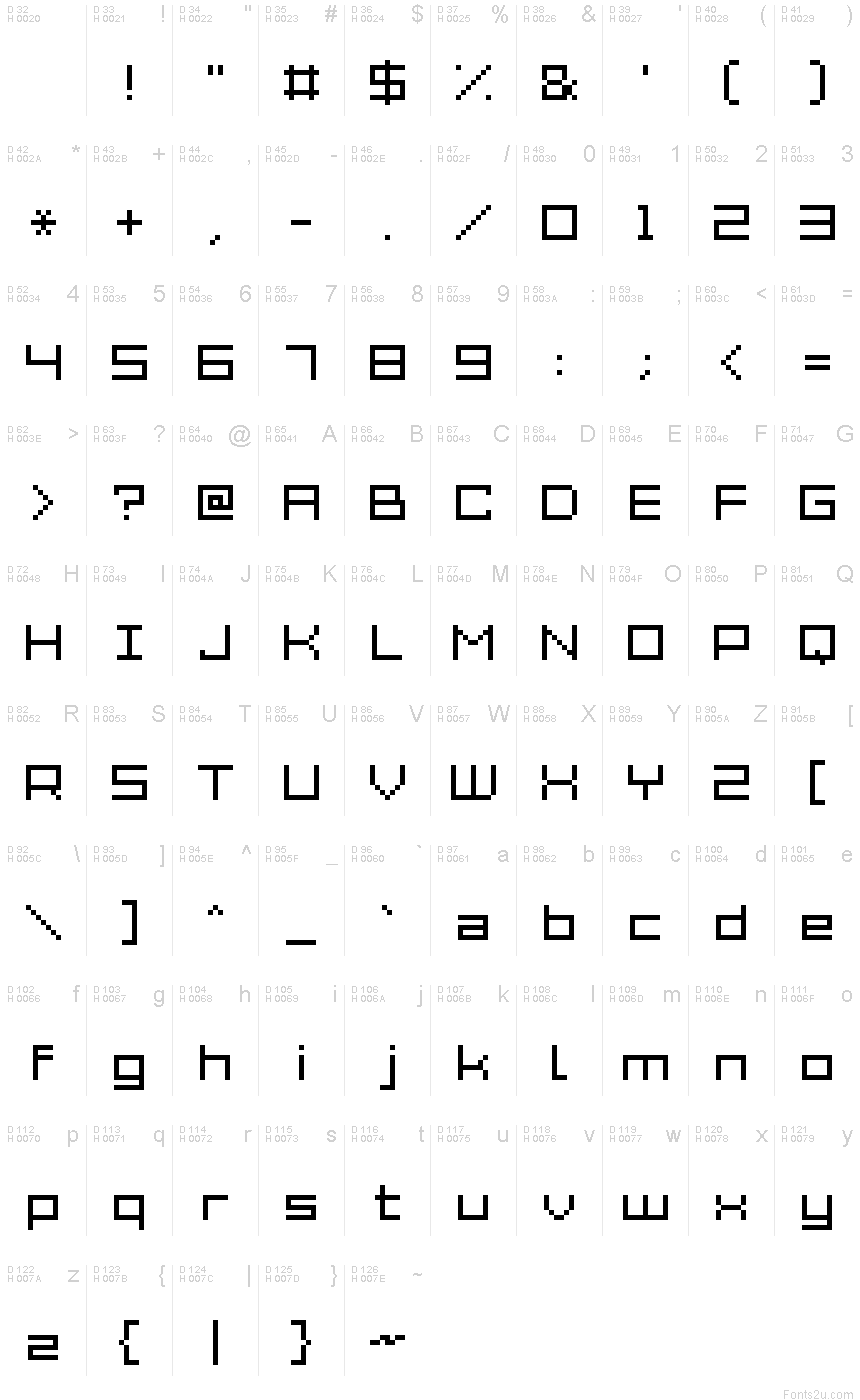
Grixel Acme 7 Wide Xtnd
Grixel Acme 7 Wide Xtnd od Grixel - Greek Pixel Fonts to darmowy, pixelowy krój bitmapowy o wyraźnej, rozciągniętej estetyce, nawiązującej do przewijanych ekranów gier. Jego bardzo szerokie proporcje, ostre pociągnięcia o grubości jednego piksela i ciasny rytm nadają każdemu słowu charakter migającego banera – niczym zamrożona w ruchu klatka z ekranu demonstracyjnego retro. Litery pozostają niezwykle czytelne nawet przy bardzo małych rozmiarach, dzięki czemu uzyskujesz ostrą, rastrową teksturę bez zbędnego szumu wizualnego.
Dzięki Grixel Acme 7 Wide Xtnd nadasz spójny, futurystyczny klimat interfejsom gier retro (HUD), logotypom sci-fi, plakatom vaporwave, stronom z pixel artem, nakładkom do streamowania oraz okładkom albumów synthwave. Ten darmowy font świetnie sprawdza się w krótkich hasłach lub etykietach interfejsu; w przypadku dłuższych tekstów warto zestawić go z prostszym krojem typu pixel sans lub mono w nieco mniejszym rozmiarze. Aby uzyskać jak najlepszy efekt, upewnij się, że rozmiar obszaru roboczego i fontu jest ustawiony na pełne wartości pikseli, co zapewni idealną ostrość linii siatki.